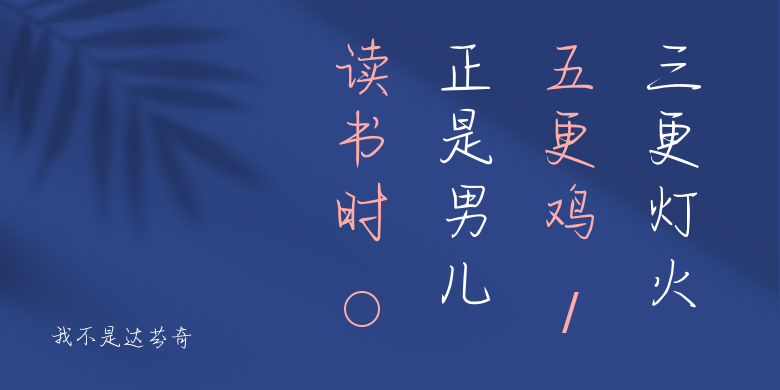
我不是达芬奇
我不是达芬奇,这款字体结构工整、笔画清晰,兼顾美观与易读性,适用于标题、正文、海报、包装、LOGO 等多种场景。字形优雅稳定,风格百搭耐看,适配日常排版与创意设计,让文字呈现更舒适、更具质感。我不是达芬奇一笔一画,皆是细节,以均衡的比例、流畅的线条打造舒适视觉体验,字形端正大气,风格简约现代。无论是商业设计、品牌宣传还是日常排版,都能轻松驾驭,让文字更有格调与力量。我不是达芬奇字体下载。